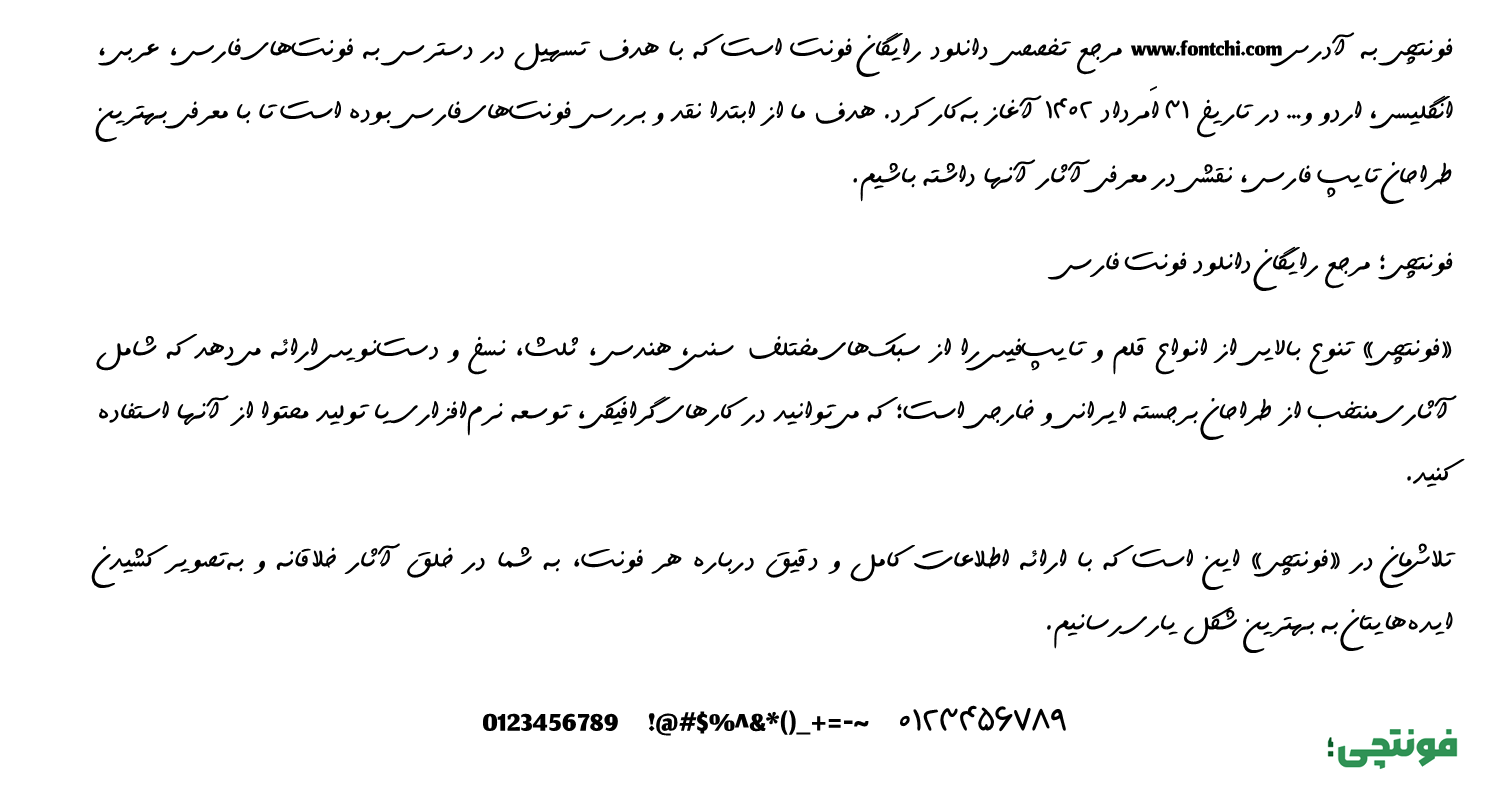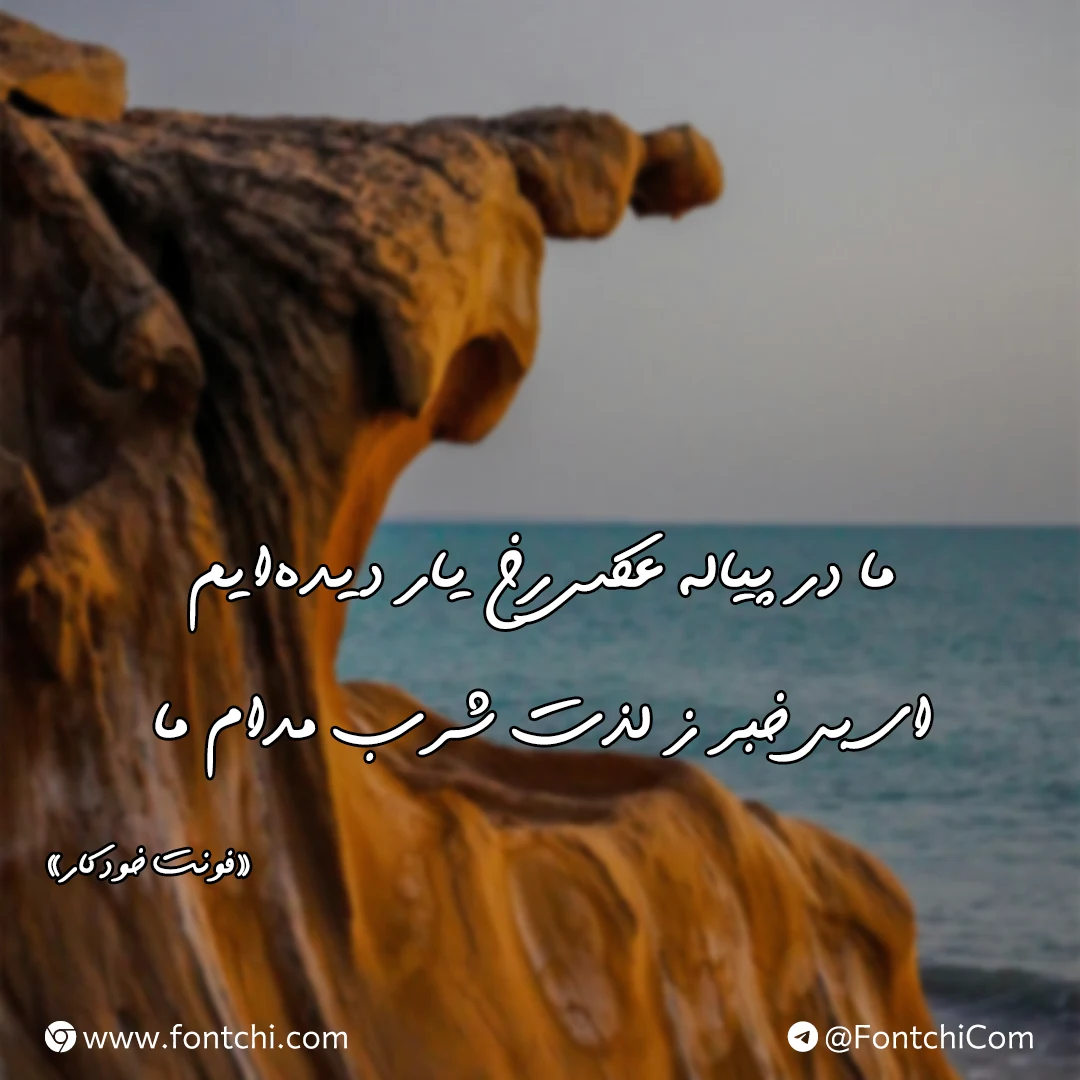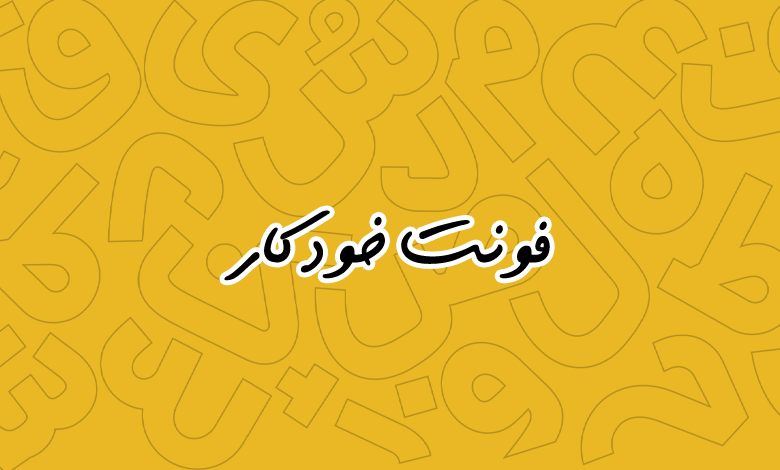
فونت خودکار (Far Khodkar)
| نام | خودکار |
| نام نمایشی | Far Khodkar |
| طراح | ابوالفضل سیل سپور |
فونت خودکار (به انگلیسی: Far Khodkar) از فونتهای دستنویس فارسی است که توسط ابوالفضل سیلسپور طراحی شده و به دلیل سبک خودکاری و صمیمیاش، به یکی از فونتهای غیررسمی محبوب در بین کاربران فارسی زبان تبدیل شده است.
این فونت با وزن Regular ارائه شده و به طور خاص برای پروژههایی که نیاز به حس و حال دستنوشتههای طبیعی و خودمانی دارند، طراحی شده است. از جمله کاربردهای این فونت میتوان به استفاده در عکس نوشته شبکههای اجتماعی یا حتی قراردادهایی که جنبه دستنویسی دارند اشاره کرد. در ادامه، به بررسی ویژگیها، کاربردها، نقاط قوت و ضعف این فونت فارسی میپردازیم.
اگر به دنبال فونت خودکاری آبی به سبک دست نوشتههای خودکار بیک هستید، این فونت همان چیزی است که به دنبالش هستید. یک فونت دستنویس با استایل خودکاری که حس نوشتن با خودکار روی کاغذ را منتقل میکند.
فونت far khodkar از زبان فارسی پشتیبانی کاملی دارد و با توجه به یکسان بودن با رسمخط عربی، میتوانید برای این زبان نیز از آن استفاده کنید. اما توجه کنید که پشتیبانی از برخی حروف عربی یا اعداد عربی «٠٤٥٦» در این قلم گنجانده نشده و از گلیفهای استاندارد فارسی استفاده میشود.
این فونت دست نویس خودکاری به دلیل نزدیکی که به دستخط انسانی دارد، دارای ظاهری کاملا صمیمی است که برای نوشتههای عمومی قابل استفاده است. در متون کوتاه تا متوسط میتوان از آن استفاده کرد؛ اما برای متون خیلی بلند توصیه نمیشود.
فونت فارسی خودکار از یک وزن معمولی Regular پشتیبانی میکند که دارای ضخامتی عادی است. ساختار طراحی قلم طوری است که در اندازههای بزرگتر خود را بهتر نشان میدهد.